Десятичная запятая в рукописном шрифте: как не спутать разделители
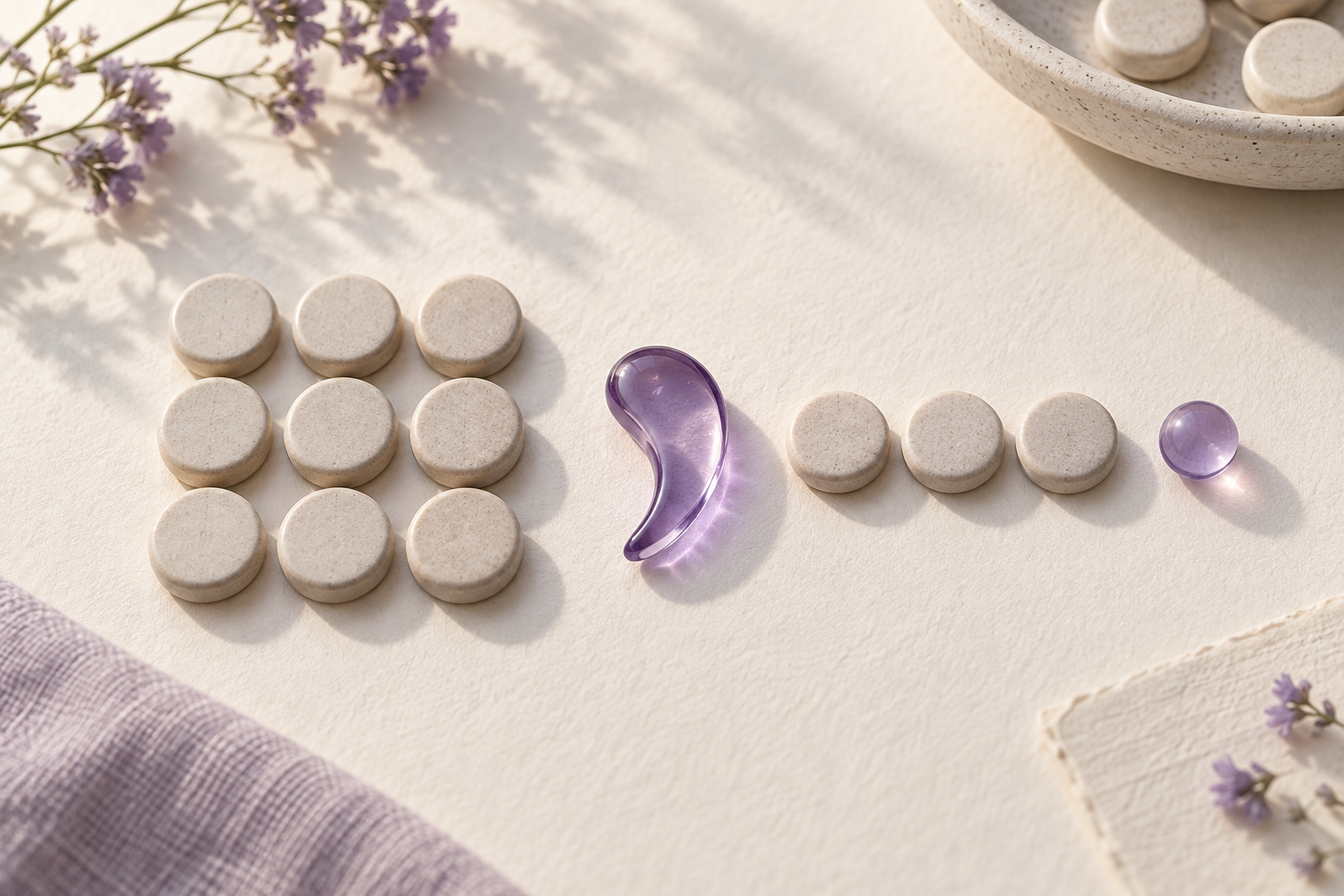
Десятичная запятая в рукописном шрифте должна отделять дробную часть числа, не превращаясь в точку, штрих или случайную отметку. Проектируйте её вместе с цифрами и проверяйте на реальных значениях: так читатель отличит 12,5 от 125 и увидит, где заканчивается целая часть. Ниже — порядок разработки, примеры и контрольный список.
Сначала определите, где будут читать числа
Запятая в цифрах — маленький знак с большой нагрузкой: неверно выбранная высота или слишком короткий хвост меняют чтение всего значения. До рисования решите, кто и где увидит набор: в заметке от руки, в печатной подписи, в таблице результатов, в рецепте, цене, измерении или подписи к диаграмме. Это влияет на размер знака, интервал и окружение.
Для короткой надписи крупным кеглем важнее согласовать жест с остальными знаками. В таблице или подписи к оси запятая может занимать всего несколько пикселей после уменьшения, поэтому важны ясный силуэт и стабильное положение. Для текста, набранного разными языками, заранее задайте локаль и примеры: Unicode описывает запятую U+002C и точку U+002E как символы с разделительной функцией, применение которых зависит от локали. Описание знаков Unicode помогает не путать код символа и его типографическое использование.
Составьте короткий список типичных чисел из будущего проекта. Например: 0,5; 12,75; 1 250,00; −0,4; 3,14 × 2. Не нужно начинать со всего диапазона цифр: важнее увидеть запятую после узкой 1, рядом с округлыми 0, 6, 8, а также с верхней или нижней выносной частью рукописной цифры. Если проект включает только целые числа, десятичный знак может не быть первоочередным; если встречаются измерения или дробные количества, он становится частью базового набора.
Чем десятичная запятая отличается от других разделителей
Один и тот же знак препинания может выглядеть похоже на запятую в прозе, но в числе он подчиняется другому ритму. В предложении знак отделяет части фразы, а в числе делит целую и дробную часть. Поэтому нельзя просто уменьшить запятую из обычного набора и считать задачу решённой: проверьте, остаётся ли её хвост видимым на нужном размере и не притягивает ли он соседнюю цифру.
Не смешивайте три задачи:
- десятичный разделитель отделяет целую часть от дробной:
12,5; - разделитель групп разрядов облегчает чтение длинного целого числа:
1 250; - знак препинания в тексте задаёт паузу или структуру фразы.
В русскоязычной редакционной публикации ГОСТ Р 7.0.110–2025, пункт 13.11, предписывает использовать запятую между целой и дробной частями числа. Стандарт действует с 1 января 2026 года и относится к авторским и издательским оригиналам непериодических, периодических и продолжающихся изданий. Он не отменяет настройки интерфейса или правила конкретной отрасли: в данных, программном коде, международном обмене и локализованных интерфейсах разделитель выбирают по принятой спецификации. Перед выпуском проверьте её у заказчика. Карточка стандарта в Росстандарте.
Для оформления больших чисел не заменяйте группировку разрядов дополнительными запятыми автоматически. В редакционном тексте обычно применяют пробел между группами цифр, чтобы 1250 не выглядело как дробь 1,250. Сверьтесь с редакционными правилами и тестируйте составные варианты: десятичная запятая плюс пробел между тысячами, знак минуса, единица измерения или процентный знак. Так становится ясно, достаточно ли одной нарисованной формы или проекту нужны отдельные интервальные настройки.
Как построить форму знака
Начните с простого силуэта. Возьмите запятую из обычного текста как ориентир, но сопоставьте её с цифрами шрифта: толщиной основных штрихов, наклоном, контрастом и характером окончания линии. У спокойного округлого письма хвост может мягко изгибаться; у угловатого маркерного почерка он может быть короче и собраннее. Это не обязательные стилистические рецепты: форма должна поддерживать именно выбранные цифры.
Проверьте три оптических параметра. Первый — положение верхней части: знак должен узнаваемо начинаться возле базовой линии цифр, а хвост — уходить ниже неё. Второй — длина и направление хвоста: слишком короткий может стать точкой, слишком длинный может зрительно соединить цифры. Третий — ширина: знак не должен казаться отдельной высокой цифрой или занимать столько же места, сколько крупная 0, если этого не требует характер гарнитуры.
Установите его относительно базовой линии, высоты строчных цифр и нижних выносных элементов. В рукописном шрифте естественная вариативность иногда меняет высоту знака при каждом написании; для шрифтового набора нужна повторяемая оптическая позиция. Сравните запятую рядом с 1, у которой мало бокового объёма, и возле 8, у которой силуэт плотнее. Если знак будто проваливается вниз в одном случае и прилипает к цифре в другом, корректируйте не только его контур, но и боковые интервалы.
Не делайте знак настолько похожим на точку, что 12,5 превращается в визуально неуверенное 12.5. Проверьте небольшой кегль, серый цвет и печать на выбранном материале: тонкий хвост может потеряться при уменьшении или заполниться краской. Одновременно не утолщайте его вслепую. Если запятая превращается в тяжёлую каплю, отношение её площади к соседним цифрам становится слишком заметным. Оценивайте общий рисунок числа, а не отдельный увеличенный глиф.
Соберите основу шрифта и сравнивайте все символы на одинаковых контрольных строках. Для рукописного набора можно подготовить шаблон в Fontgenerator, оцифровать образцы и проверить, как запятая работает рядом с каждой цифрой.
Десятичная запятая работает, когда её силуэт виден, положение повторяемо, а интервалы согласованы с цифрами. Выберите формат по задаче, проверьте запись на реальных носителях и сохраните контрольные строки. Если вы собираете собственный рукописный набор, создайте шаблон букв, цифр и знаков в Fontgenerator и испытайте их вместе, а не по отдельности.